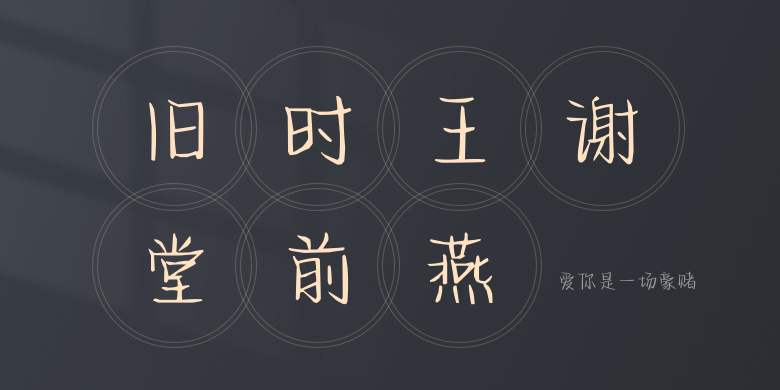
爱你是一场豪赌
爱你是一场豪赌,这款字体结构工整、笔画清晰,兼顾美观与易读性,适用于标题、正文、海报、包装、LOGO 等多种场景。字形优雅稳定,风格百搭耐看,适配日常排版与创意设计,让文字呈现更舒适、更具质感。爱你是一场豪赌一笔一画,皆是细节,以均衡的比例、流畅的线条打造舒适视觉体验,字形端正大气,风格简约现代。无论是商业设计、品牌宣传还是日常排版,都能轻松驾驭,让文字更有格调与力量。爱你是一场豪赌字体下载。